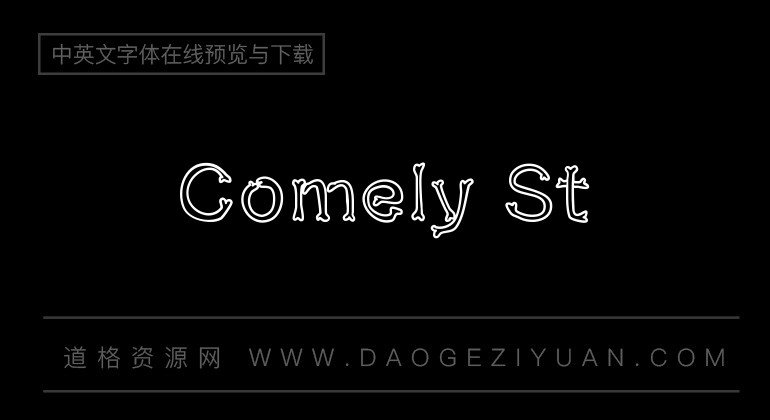
Comely St 是一款专为设计师而设计的现代字体,它拥有清晰的线条和强大的设计感,可以很好地满足您的设计需求。它有着强烈的可读性,使用它可以让您的文字更加突出,而且它的字体结构非常紧凑,可以节省您的设计空间。此外,它还支持多种字体格式,可以满足您的不同设计需求。内容介绍
Comely St是一款非常不错的手写艺术字体,具有很好的视觉感,适合于文化类的宣传设计、商业类品牌的广告和产品包装设计以及个性化文字排版等较多场景。